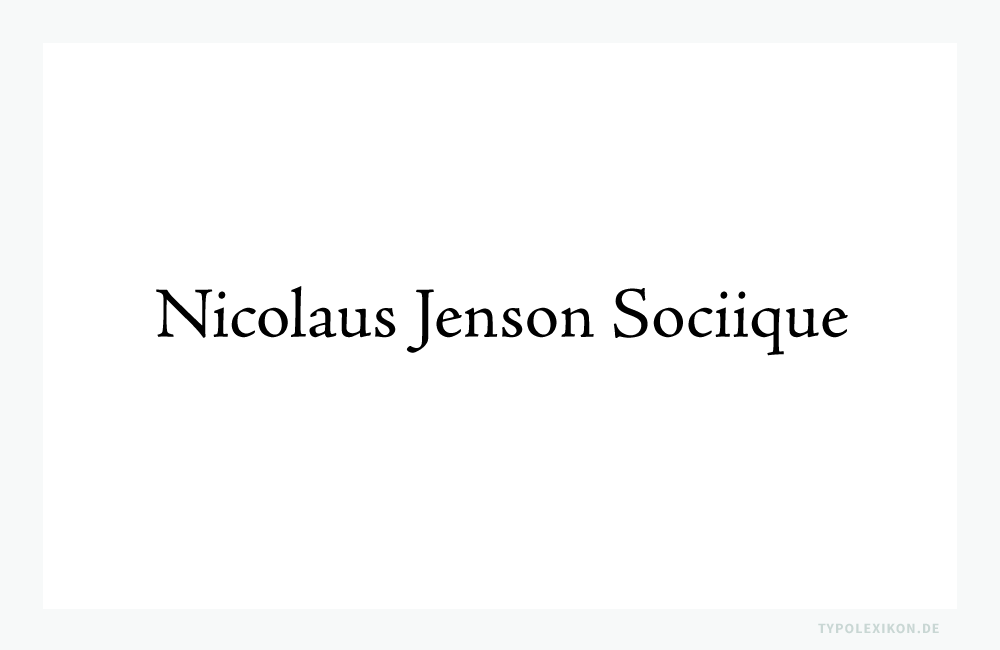
Jenson, Nicolas
Französischer Kupferstecher, Graveur und Typograf. Nicolas Jenson wurde um 1420 im französischen Dorf Sommevoire im Departement Aube in der Champagne (heute Grand Est) geboren. Er starb 1480 in Venedig. Jenson gilt als der wesentliche Schöpfer der »Litterae Venetae« (Venezianische Lettern), die als die erste vollkommen ausgebildete Reinform einer gedruckten Antiqua gelten. Diese Venezianische Renaissance-Antiqua hat die (Antiqua)Schriftkultur Europas bis heute nachhaltig geprägt. Alternative Schreibweisen seines Namens: Nicolaus Jenson und Nikolas Jenson.
Nach seiner Ausbildung zum Graveur in den Münzwerkstätten von Troyes (heute Region Grand Est, Départements Aube im Nordosten Frankreichs) wirkte er zunächst als Münzmeister in der Monnaie Royale, der Königlichen Münze, in Tours (heute Region Centre-Val de Loire, Départements Indre-et-Loire).
Die Venezianische Renaissance-Antiqua »Jenson Pro« in normalen Schriftschnitt (Regular) von Adobe®.
Hier erreichte ihn im Oktober 1458 eine Order des französischen Königs, in der Charles VII. (1403–1461) seine Münzmeister anwies, verständige Fachleute auszuwählen und heimlich nach Deutschland zu schicken, damit diese bei Johannes Gutenberg (um 1400–1468) in Mainz die Typografie erlernten und die Fähigkeit erlangten, die neue »Deutsche Kunst« im Königreich Frankreich auszuüben: 1)
(…) Le IIIe jour d’octobre mil IIII° LVIII ledit sr roy ayant entendu que messire Jehan Guthenberg chevalier demourant à Mayence pais d’Allemaigne (… ) avoit mis en lumiere l’invencion d’imprimer par poinçons et caracteres (…) auroit mandé aux generaulx de ses monnoyes lui nommer personnes bien entendues a ladite taille et pour envoïer audit lieu secrettement soy infformer de la dicte forme et maniere de ladite invencion, entendre, concevoir et apprendre l’art d’icelle (…)
Jenson realisierte die Chance und begab sich daraufhin selbst nach Mainz und wurde, da Gutenberg im Rechtsstreit die Werkstatt an seinen Geldgeber Johann Fust (um 1400–1466) bereits schon 1454 verloren hatte, vermutlich ab 1859 in die Fust’sche Offizin – infolge Fust-Schöffer´sche Offizin – aufgenommen, wo er genauso wie alle übrigen Adepten auf die Bibel Geheimhaltung schwören musste, bevor er von seinem Lehrmeister Peter Schöffer (um 1425/1430–1502/1503) in die »Deutsche Kunst« eingeweiht wurde. 2)
Jenson lernte in der Mainzer Offizin des Johann Fust u.a. auch die Prototypografen Arnold Pannartz (o.A.–um 1476), Conrad Sweynheym (o.A.–um 1474/1477) und Ulrich Zell (o.A.–nach 1507) kennen.
Nach der gewaltsamen Einnahme von Mainz durch die Truppen des von Papst und Kaiser favorisierten Adolf von Nassau (um 1423–1475), mussten in der Nacht vom 28. Oktober 1462 Nicolas Jenson und seine Kollegen die Offizin im Humbrechthof (die Keimzelle der Prototypografie) geradezu fluchtartig verlassen, da Fust und Schöffer Günstlinge des nunmehr abgesetzten Erzbischofs Diether von Isenburg (1412–1482) gewesen waren.
Jensons Spuren verlieren sich immer wieder für kurze Zeit. Nach Frankreich, wo inzwischen der wenig kunstsinnige Ludwig XI. (1423–1483) seinem Vater Charles VII. auf dem Thron nachgefolgt war, kehrte er allerdings nicht mehr zurück.
Möglicherweise arbeitete er ab 1462/1463 in der in Köln am Rhein neu gegründeten Offizin von Ulrich Zell (o.A.–nach 1507) und zog dann um 1464 mit Pannartz und Sweynheym nach Italien bzw. reiste dann nach Venedig weiter, wo er um das Jahr 1468 erstmals nachweislich in Erscheinung trat. Ob er in Mailand bei dem Typografen Dionysius Paravisinus (o.A.) oder in Subjaco (Latium) bei Pannartz und Sweynheym Zwischenstopps einlegte, lässt sich nur vermuten.
Sicher ist erst wieder, dass Nicolas Jenson in Venedig zunächst für Johannes von Speyer (o.A.–1469/1470) – infolge für seinen Bruder Wendelin (o.A.–1477) – als Werkmeister arbeitete. Johannes von Speyer gründete 1469 die erste Druckerei in Venedig. 3) Wie lange er für die Officina de Spira arbeitete, ist ungewiss; vermutlich jedoch von 1469 bis 1475.
Zusammen mit Johannes und Wendelin von Speyer (Giovanni and Vendelino da Spira) entwickelte er ab 1468 aus der »Sublacensischen Antiqua« von Arnold Pannartz und Conrad Sweynheym die »Litterae Venetae« (Venezianische Antiqua). Sie gilt als die erste vollkommen ausgebildeten Reinform einer gedruckten Antiqua von exemplarischer Ausgewogenheit, Deutlichkeit und betonter Rundheit in der Buchstabenkomposition.
1470 druckte Jenson erstmals in dieser neuen Type die »Praeparatio Evangelica« (»Die Vorbereitung auf das Evangelium« in fünfzehn Bänden) des Bischofs Eusebius von Caesarea (um 260/64–339/340). Woraufhin dieser Schrifttypus in ganz Italien nachgeahmt wurde und als legendäre »Jenson Antiqua« des venezianischen Typus, der sogenannten Venezianischen Renaissance Antiqa, in die Geschichte der Typografie einging.
Eine Schriftprobe (Schnellwertskizze) der Litterae Venetae (Venezianische Antiqua) von Nicolas Jenson (um 1420–1480), wie sie um 1475 bei der Gründung der Offizin »Nicolaus Jenson Sociique« (Nicolaus Jenson und Gefährten) in Gebrauch war.